「リリック(歌詞字幕)」にぴったりの日本語フリーフォント
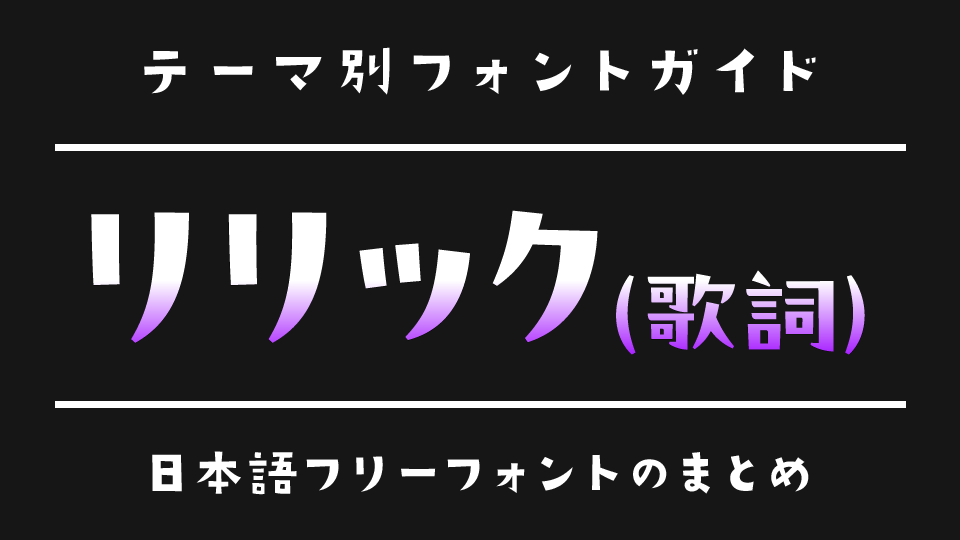
今回は、MVやリール動画、ショート映像で使える「リリック(歌詞字幕)」にぴったりな日本語フリーフォントをご紹介します。
リリック字幕は、音楽と映像の雰囲気をつなぐ重要な要素。フォントの選び方ひとつで、歌詞の伝わり方も印象も大きく変わります。切なさや儚さを表現する繊細な手書き風、ポップで明るい印象を与える丸文字、クールで疾走感のあるサンセリフなど、楽曲の世界観に寄り添うフォント選びが鍵になります。
今回は、リリック動画やVlog、歌詞付きショートコンテンツに最適な、個性と可読性を兼ね備えた日本語フリーフォントを厳選しました。音楽の魅力をフォントでさらに引き立てたい方は、ぜひチェックしてみてください。
リリック字幕にぴったり!歌詞が映えるおすすめフリーフォント
以下のサンプルのように、MVや動画制作では、リリック(歌詞字幕)の見せ方によって作品の印象が大きく変わります。楽曲の世界観や感情をより魅力的に伝えるためには、映像だけでなくフォント選びも重要なポイントです。
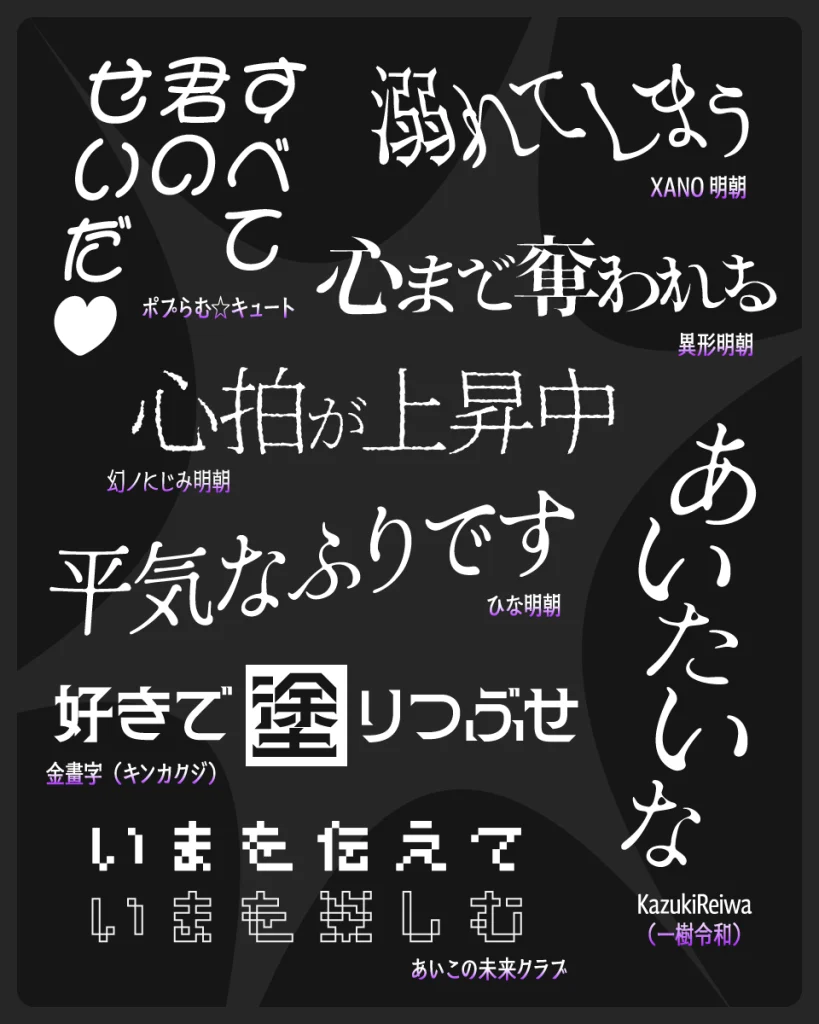
一樹令和
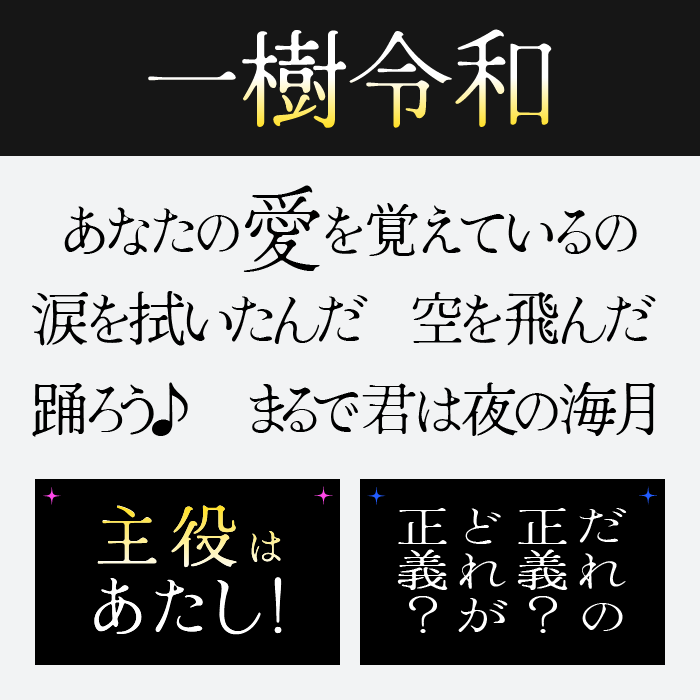
| おすすめの歌詞 | 季節を描く歌詞、情景描写、和風表現、人生を語る歌詞 |
一樹令和フォントは、繊細な筆のような縦長の骨格が調和した、どこか儚げな雰囲気をまとうフォントです。愛や別れ、感情の起伏をそっと語りかけるような歌詞と相性が良いフォントです。
くらむぼん
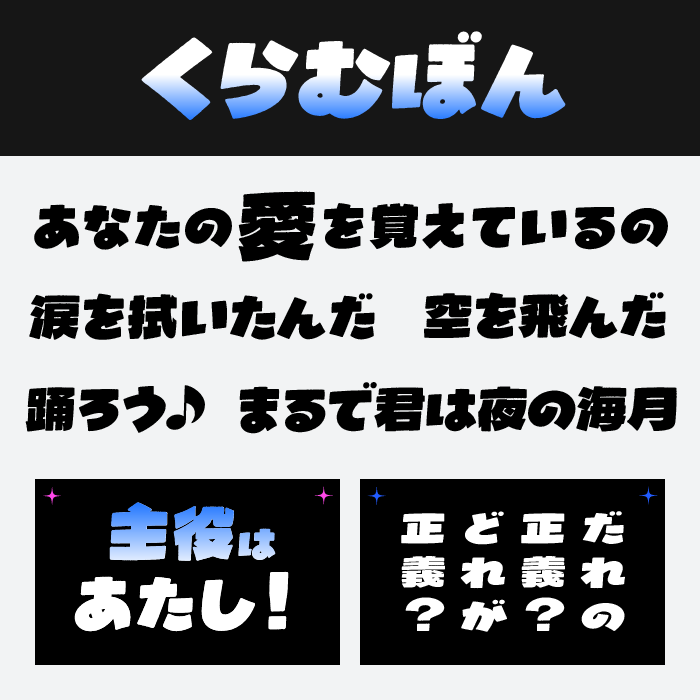
| おすすめの歌詞 | 前向きなメッセージ、応援ソング、サビのフレーズ、元気な掛け声 |
くらむぼんフォントは、跳ねるような文字のリズム感が魅力で、見る人の気持ちを明るく盛り上げるエネルギーがあります。楽しさや元気な恋を描いた歌詞にぴったりなフォントです。
白光明朝
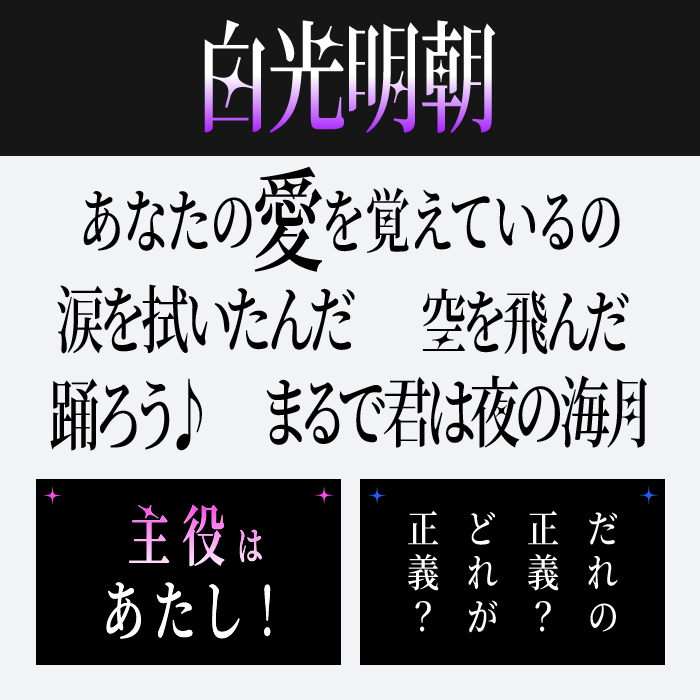
| おすすめの歌詞 | 運命を語る歌詞、孤独や葛藤の表現、世界観重視の歌詞、物語調のフレーズ |
白光明朝は、シャープな縦線と独特な装飾が特徴の個性的な明朝体フォントです。一般的な明朝体よりも幻想的で存在感があり、歌詞そのものを印象的に見せたい場面に向いています。少しダークな世界観や文学的な表現とも相性が良く、映像に強い余韻を残せるフォントです。
星のモチーフは一部の文字にだけ散りばめられており、文章を打ち込むとさりげなく星が現れ、幻想的な雰囲気を楽しめるフォントです。
ゴチカクット
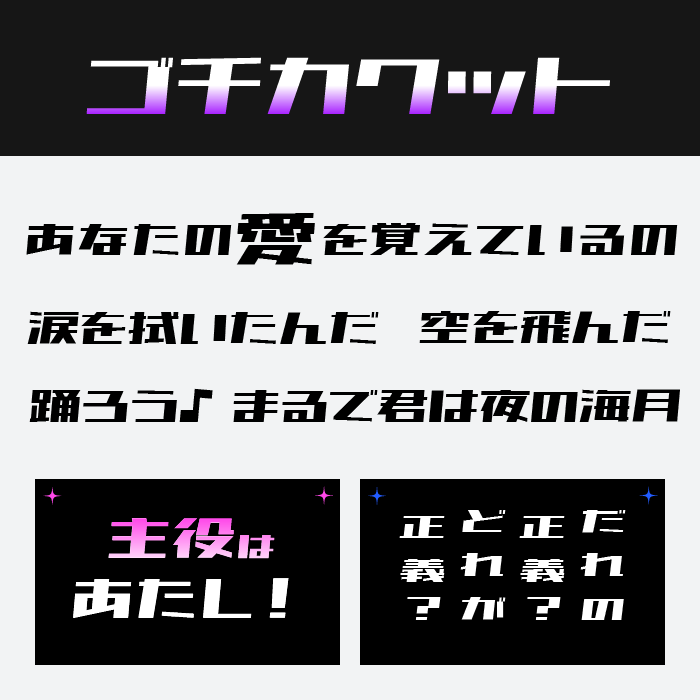
| おすすめの歌詞 | 疾走感のある歌詞、都会的な表現、未来を描くフレーズ、クールなサビ |
ゴチカクットは、未来感のあるシャープなデザインが特徴のゴシック体フォントです。文字にスピード感やデジタル感があり、現代的な映像演出との相性に優れています。クールな世界観や近未来的な楽曲の歌詞字幕として活躍するフォントです。
テガキカクット
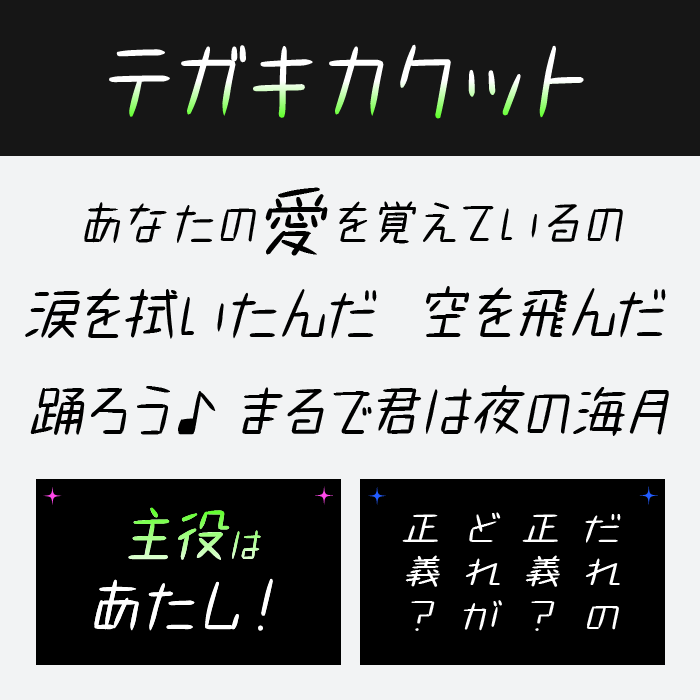
| おすすめの歌詞 | 日常を描く歌詞、恋愛ソング、素直な気持ちの表現、語りかけるような歌詞 |
テガキカクットフォントは、手書きのような繊細さとカクカクした線が絶妙に混ざり、言葉の温度を丁寧に伝えてくれます。切なさや想いを込めたバラードに向いているフォントです。
解星デコール
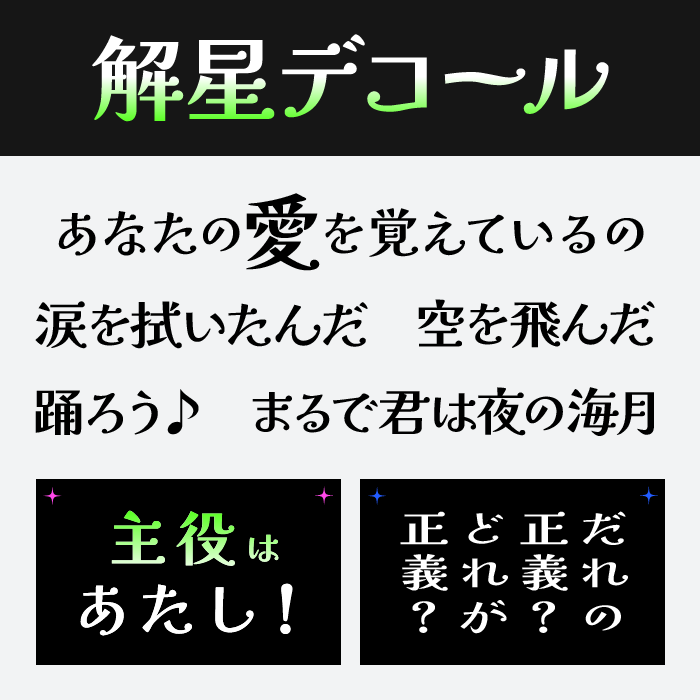
| おすすめの歌詞 | 恋愛ソング、切ないフレーズ、感情を語る歌詞、印象的なサビ |
解星デコールフォントは、明朝体の凛とした美しさの中にキラリと光る個性があり、感情の深さと演出力のある歌詞に合います。プリンセス系の舞台映えするようなリリックと好相性なフォントです。
せのびゴシック
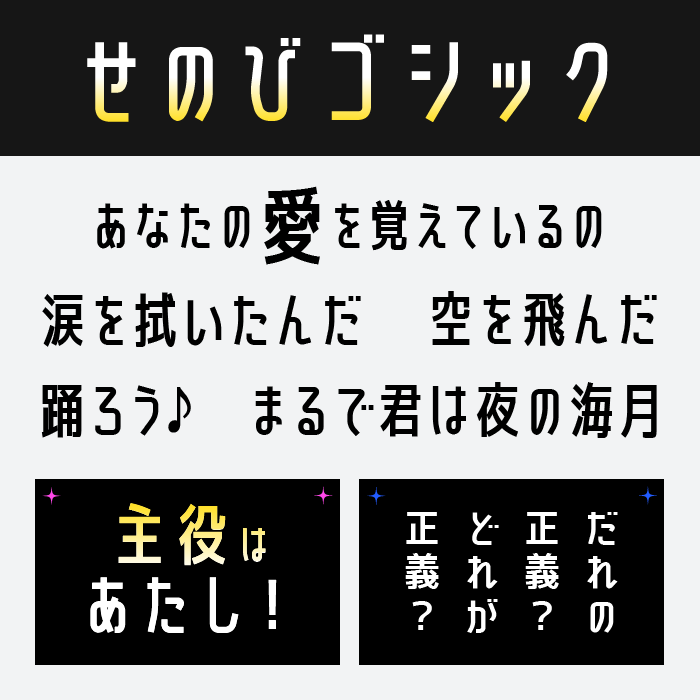
| おすすめの歌詞 | サビのフレーズ、印象的なワンフレーズ、都会的な歌詞、恋愛ソング |
せのびゴシックは、縦長のシルエットが印象的なゴシック体フォントです。スタイリッシュで洗練された雰囲気があり、歌詞をすっきりと見せることができます。シンプルながら映像映えするため、幅広いジャンルのMVで使いやすいフォントです。
ふい字フォント
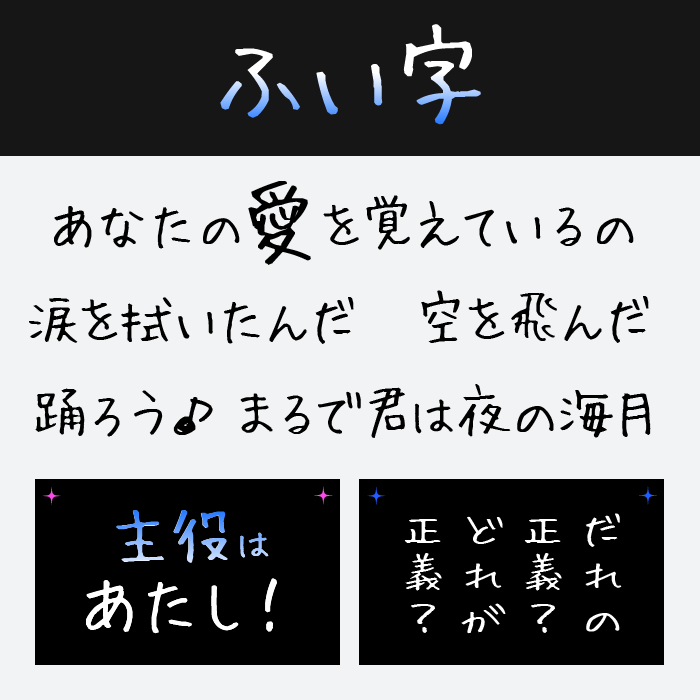
| おすすめの歌詞 | 感謝の言葉、恋愛ソング、思い出を語る歌詞、手紙のような歌詞 |
ふい字フォントは、手書きならではの柔らかさとちょっぴり切ない表情が魅力で、飾らない言葉に心を込めたい時にぴったりです。あたたかく寄り添うような歌詞に映えるフォントです。
アームド・レモン
| おすすめの歌詞 | 本音の言葉、日常の描写、青春の葛藤、等身大のメッセージ |
アームド・レモンフォントは、やや崩したような手書きのラインに可愛さと尖りが絶妙なバランスのフォントです。無垢な感情や不器用な恋心を歌うリリックと合わせたいフォントです。
源暎きわみゴ
| おすすめの歌詞 | サビの歌詞、応援メッセージ、前向きなフレーズ、盛り上がるパート |
源暎きわみゴフォントは、太く存在感のある文字に絶妙な丸みが加わり、力強さとやさしさを兼ね備えています。大切な一言をインパクト強く届けたいときに最適なフォントです。
ましゅまろポップフォント
| おすすめの歌詞 | 恋する気持ち、かわいいフレーズ、ハッピーな歌詞、応援ソング |
ましゅまろポップフォントは、ふわっとした丸みと独特の軽やかさがあり、ポップでかわいらしい世界観を演出できます。恋や夢をテーマにした甘めのリリックにぴったりなフォントです。
流怪譚
| おすすめの歌詞 | 情景描写、幻想的な歌詞、物語調のフレーズ、和風表現 |
流怪譚フォントは、明朝体をベースとして、歪んだ鋭い払いが混じる、情念を帯びた風格のあるフォントです。濃淡のある線のリズムが、ドラマチックな歌詞にぴったりの抑揚を添えてくれるフォントです。
しねきゃぷしょんフォント
| おすすめの歌詞 | 感謝の言葉、恋愛ソング、思い出を振り返る歌詞、語りかけるようなフレーズ |
しねきゃぷしょんは、手書きらしい自然な線と高い可読性を兼ね備えたフォントです。字幕としても読みやすく、歌詞の内容を素直に伝えたい場面に向いています。ポエティックなリリックとの相性も良い、安心感のあるフォントです。
金畫字
| おすすめの歌詞 | 都会を描く歌詞、未来的なフレーズ、スタイリッシュなサビ、機械的な世界観の歌詞 |
金畫字フォントは、縦画と横画にメリハリがある整然としたデザインが特徴で、荘厳さとスタイリッシュさを併せ持っています。強い言葉や核心のフレーズを際立たせたい歌詞にぴったりのフォントです。
ラノベポップ
| おすすめの歌詞 | 応援メッセージ、前向きな歌詞、サビのフレーズ、青春ソング |
ラノベポップフォントは、見出しにも使える太めでフラットな字形が特徴で、ストレートなメッセージをしっかり届けられます。力強さの中に軽やかさもあり、明るいリリックによく合うフォントです。
廻想体ネクスト
| おすすめの歌詞 | 哲学的な歌詞、抽象表現、世界観重視のフレーズ、近未来的な歌詞 |
廻想体ネクストフォントは、未来的な形状の中に手書き風の揺らぎを持ち合わせた個性的なフォントです。繊細なストーリー性をもつ歌詞や、少し不安定な感情を表現するのに向いているフォントです。
デラ・ゴリラ
| おすすめの歌詞 | 熱いメッセージ、叫ぶようなフレーズ、反骨精神を表現した歌詞、サビの決めフレーズ |
デラ・ゴリラは、極太のシルエットと大胆な斜めカットが特徴のインパクト抜群なフォントです。文字そのものに勢いや圧力があり、歌詞を強く印象付けたい場面で活躍します。ロックやラウドな楽曲との相性が良く、サビやキラーフレーズを力強く見せたいときにおすすめです。
えり字フォント
| おすすめの歌詞 | 恋愛ソング、日常の描写、素直な気持ちを綴った歌詞、手紙のようなフレーズ |
えり字フォントは、手書きの儚さと繊細な揺らぎが絶妙なバランスで、胸に染み込むような歌詞にぴったりです。やさしく語りかけるような雰囲気で、恋愛や切ないテーマの字幕に最適なフォントです。
ひな明朝
| おすすめの歌詞 | 恋愛ソング、切ない歌詞、情景描写、心情を語るフレーズ |